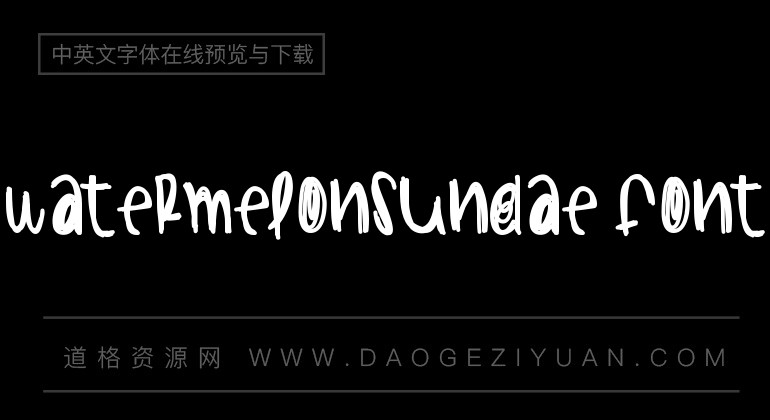
WatermelonSundae Font
WatermelonSundae Font 是一种手写风格的字体,它的设计源于日常生活中的手写字体和手绘风格。字母形状清晰,线条圆润,看起来非常温暖和亲切。 这种字体适用于多种场合,例如卡片、海报、宣传册、网页设计和商业品牌等。它的特点是非常易于阅读,同时也很具有个性和创意。 WatermelonSundae Font 的下载和使用非常简单,可以在多个字体网站上免费下载。它支持许多不同的语言和字符集,包括英文、西班牙文、德文、法文、葡萄牙文和北欧语言。
WatermelonSundae Font是一款非常不错的手写艺术字体,具有很好的视觉感,适合于文化类的宣传设计、商业类品牌的广告和产品包装设计以及个性化文字排版等较多场景。